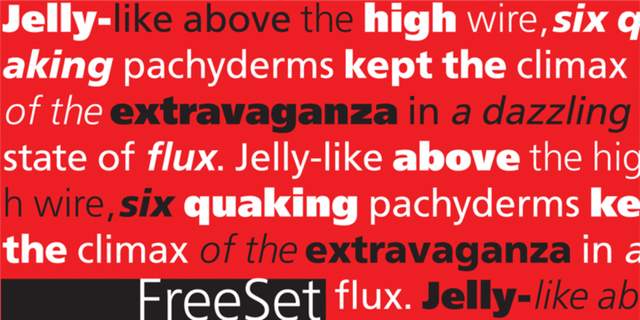
Гарнитура разработана в фирме ПараТайп (ПараГраф) в 1992 (дизайнер Тагир Сафаев) на основе рисунков шрифта Frutiger фирмы Mergenthaler Linotype, 1976 (дизайнер Aдриан Фрутигер). Frutiger первоначально был спроектирован для нового парижского аэропорта им. Шарля де Голля в Руасси. Открытый гротеск хорошо работает и в текстовом, и в акцидентном наборе. Шесть дополнительных кириллических начертаний (светлое, полужирное, сверхжирное - с наклонными) добавлены в 1998-2000 году. Мультилингвальные версии этих шести начертаний содержат Армянский алфавит, спроектированный Манвелом Шмавоняном в 1997 году. Два узких начертания (полужирное и жирное) разработаны Манвелом Шмавоняном в 2005 году.